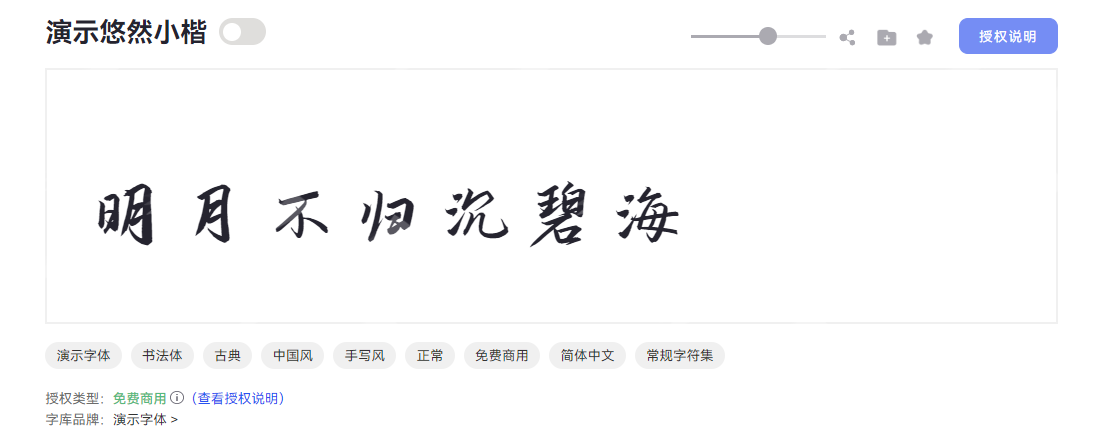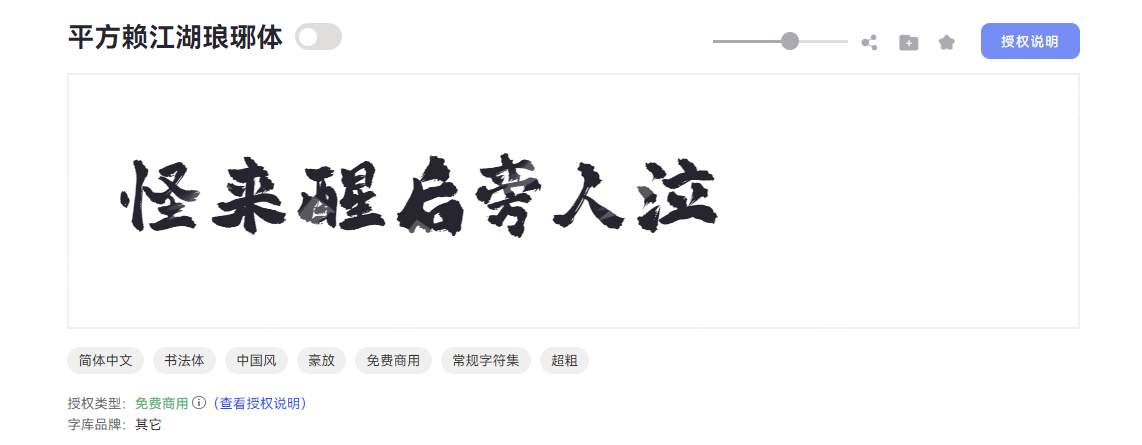
对于常年在设计行业工作的人来说,文字不仅仅是信息载体,更是设计作品的灵魂,传递创作者的情感与理念。如果选到了不合适的字体,会让你的设计作品大打折扣,甚至有可能一个字体就毁了整部作品的意境和格调。而毛笔字体就是传递情绪变化的最好的文字形式,同样也是中国传统书法艺术的重要组成部分。为了帮大家轻松规避版权纠纷,提升创作效率,本文结合字体管理神器——字由,精心整理了一份免费商用毛笔字大全,6 款毛笔字体涵盖不同设计风格,让你轻松 hold 住全场,赶紧来看看吧!
一、演示佛系体
演示佛系体是一款自带禅意气质的特色创意字体,整体看起来古典而厚重。字形结构扁宽舒展,打破了固有造字框架的条条框框,看似外表松散,实则保持相同的韵律,传递从容自在、宁静且富有生命力的感觉。字体采用居中重心设计,配合宽博中宫;笔型融入柔和圆角与圆润笔触,粗实均匀的线条既保留饱满力量感,又通过圆头笔画增添亲和温度。独特的笔画断开处理是其点睛之笔,在连贯的视觉节奏中留出巧妙呼吸空间,打破沉闷的同时更显灵动层次。
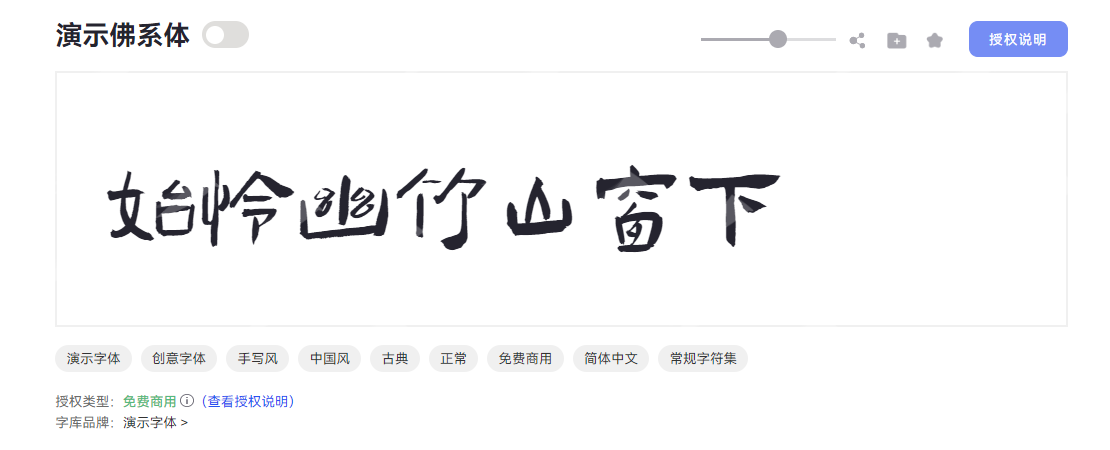
二、演示悠然小楷
演示悠然小楷是一款融合传统书法底蕴与现代设计需求的小楷字体,以悠然气质传递东方笔墨韵味,娟秀的笔触中也沉积着强劲的力量。从字形结构来看,悠然小楷笔画分明、字形修长舒展,重心平稳居中,中宫松紧适中,既保留小楷书法的端庄骨架,又通过纵向拉伸的比例增添几分灵动气韵,整体结构疏密有致,耐看且易读。最值得一提的就是笔型设计,笔画纤细圆润,圆头收笔自带毛笔书写的温润质感,起笔轻缓,行笔流畅,线条过渡自然,转折处柔和无棱角,具有极强的毛笔字书法艺术感。粗细均匀的线条搭配断开式笔画连接,让字体在精致中透着呼吸感,避免密集排版的刻板,反而如文人挥毫般从容自得,传递沉静、温润、富有书卷气的视觉语言。
三、平方赖江湖琅琊体
平方赖江湖琅琊体字体是一款带有古风气息的毛笔书法字体,核心特征就是粗重遒劲的笔触和毛笔笔刷质感,形成了很强的视觉冲击力。这款字体的字形偏向方正;线条略显粗厚饱满;转折处的棱角与飞白效果精准还原了毛笔在宣纸上挥毫泼墨的原生质感;每个笔画均保留了毛笔书法特有的笔刷效果,不仅增强了字体表现力,还使得字体更具东方韵味和江湖侠气。对于豪放不羁风格的国风设计师来说,这款字体绝对能快速提升作品质感,渲染更强的氛围感与故事感。
四、钟齐志莽行书
钟齐志莽行书是一款充满中国风韵味的手写书法字体,以流畅洒脱的笔触展现传统行书的艺术魅力。字形修长舒展,中宫宽博稳重,重心居中;笔画粗细均匀适中,通过自然的连笔与流畅弧度展现行书特有的书写韵律,起笔收笔保留手写原生质感,避免机械规整的方头或尖锋设计,让每一笔划都富有动感和生命力。最关键的就是这款字体的连笔处理,笔势豪迈,增强了文字的动感与连贯性,整体风格兼具力量感与飘逸感,为作品注入独特的东方美学气质,传递出洒脱不羁的艺术张力。
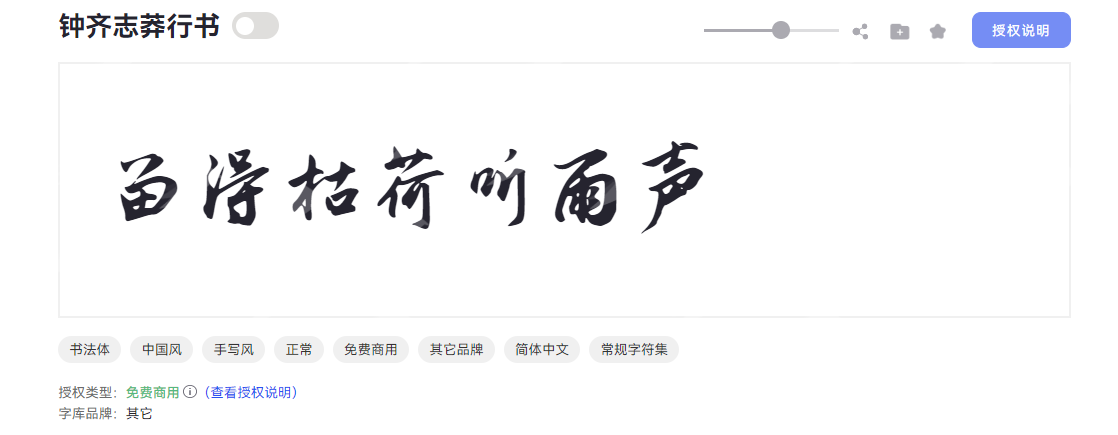
五、字由芳华体
字由芳华体是字由品牌推出的一款创意字体,以“有趣”为核心设计理念,兼具视觉张力与实用价值,整体风格怀旧而摩登,充满浓浓的艺术氛围和生活情调。字由芳华体整体字形修长,重心居中且中宫适中,灵动的轮廓打破沉闷,展现出独特的韵律感。而它的笔型设计充满巧思:笔画末端融入独特的装饰元素,搭配圆润饱满的笔画形态与部分连笔设计,让每一笔都自带趣味属性和浪漫色彩。这些细节打破了常规字体的刻板印象,融合了古典笔墨与现代排版的需求,保留毛笔的书写质感,又不失现代设计的时尚感,尽显设计师的匠心巧思。
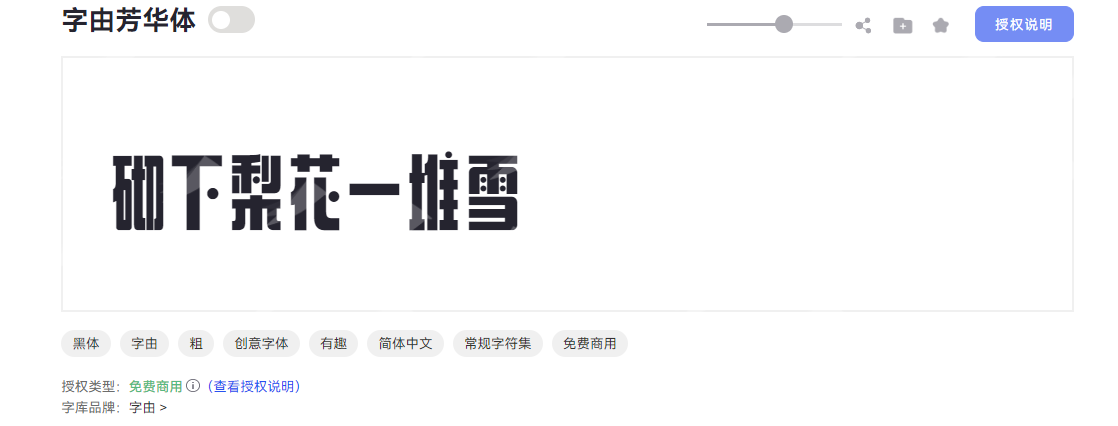
六、Aa剑豪体
剑豪体是 Aa 字库推出的一款中国风手写体,以“力量”与“豪放”为核心气质,将传统书法韵味与现代设计需求巧妙融合。作为免费商用字体,剑豪体凭借独特的字形设计,成为文化创意领域的实用之选。 字形修长劲挺,重心巧妙上移,中宫收紧的结构让字体在紧凑中透出张力;锐利的收笔或尖锐的转折宛如剑刃出鞘般利落;笔型融入利落斜切,搭配方头笔画收尾,锋芒暗藏却不失沉稳;笔画粗重均匀、硬朗锐利,多采用直线和锐利的折角;断连分明的处理既保留手写的随性,又透出剑势般的刚劲,将“侠气”与“力量”具象化。